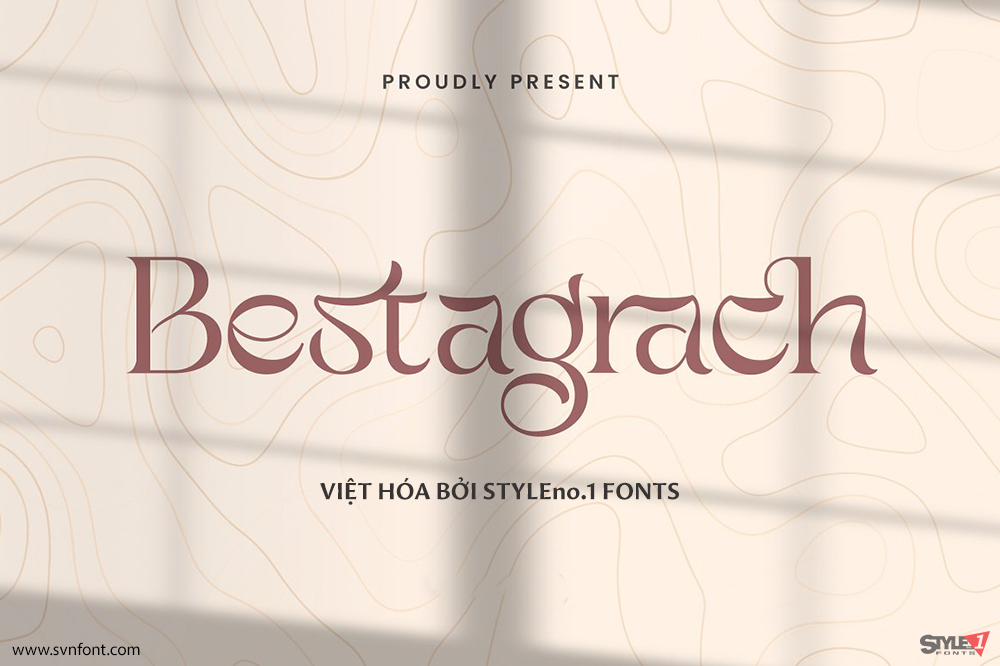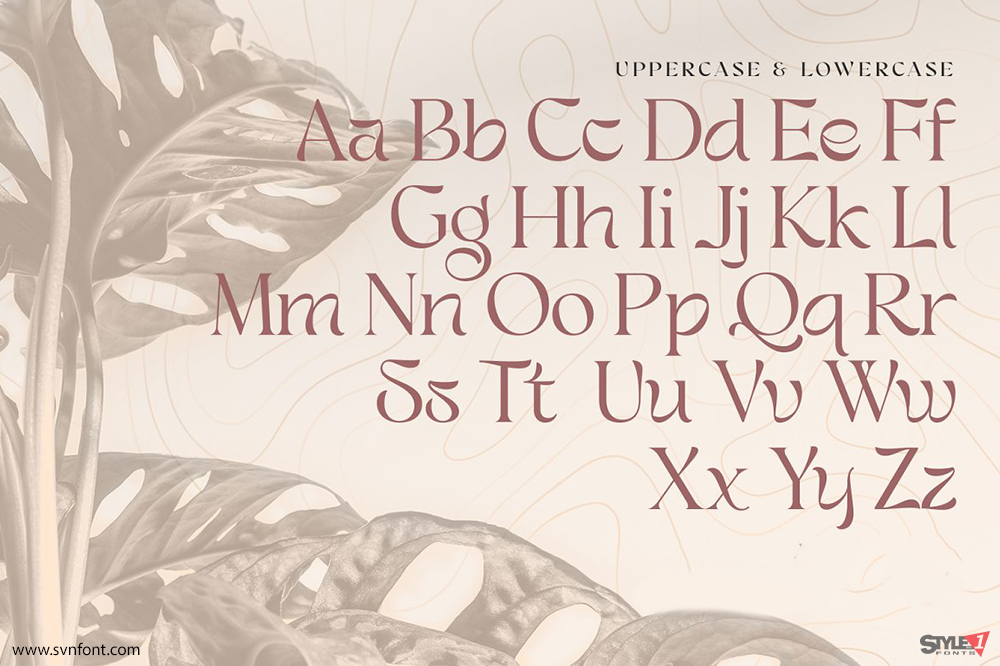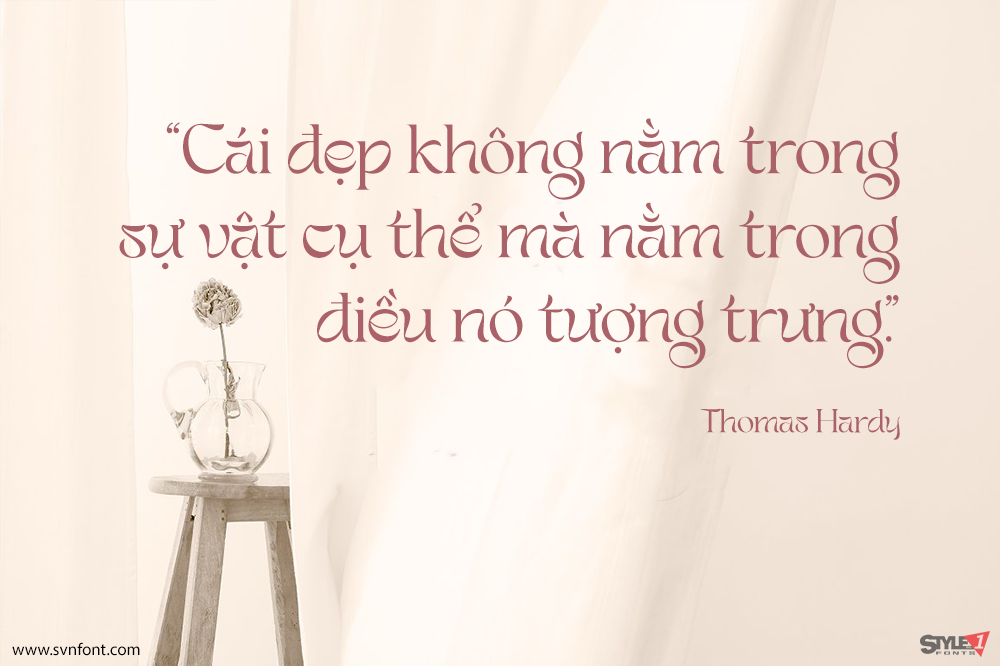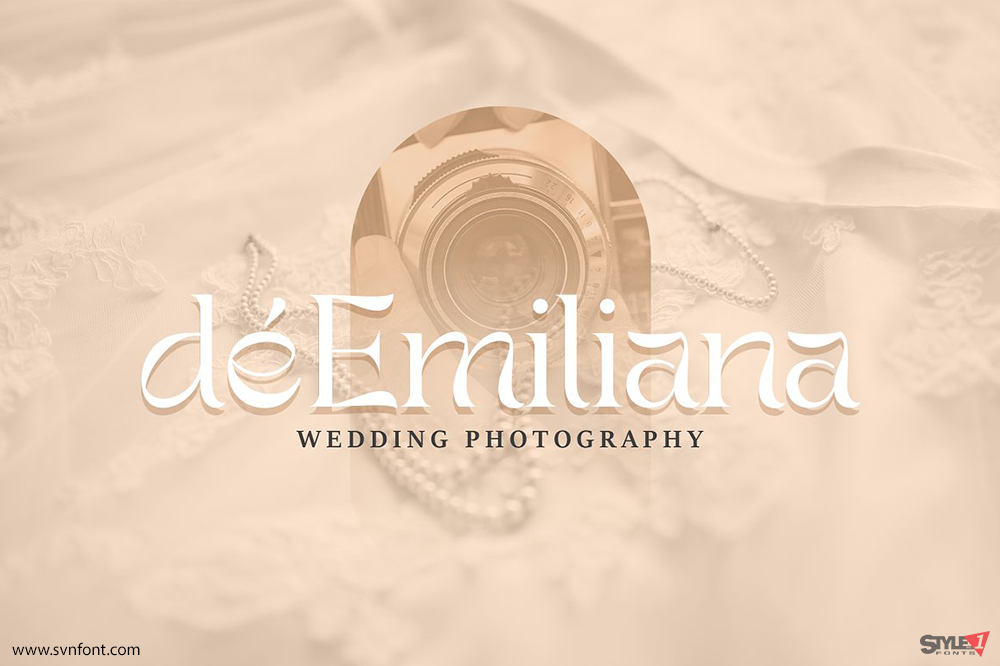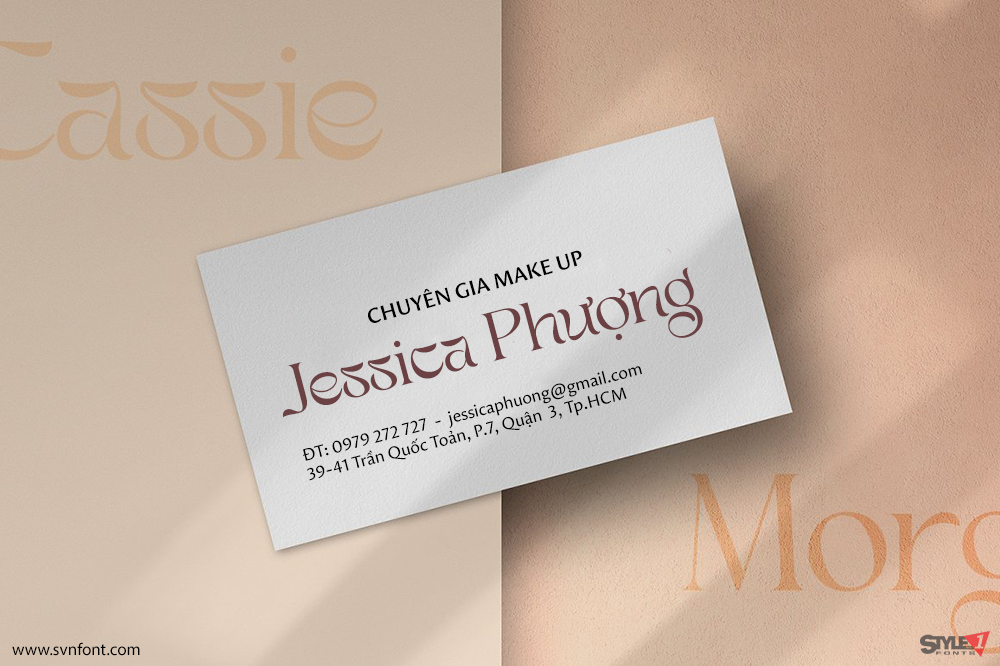
Font Việt Hóa SVN-Bestagrach Chữ Nối Sáng Tạo
Bestagrach - Chữ nối độc đáo Connected Serif là một phông chữ thanh lịch và sử dụng các chữ ghép để liên kết các chữ cái một cách trơn tru. Hoàn hảo để thêm một nét độc đáo cho biểu trưng đánh dấu từ, chữ lồng hoặc dấu ngoặc kép. Bestagrach có 12 chữ ghép và làm cho nó trở nên siêu tuyệt vời. Có thể tắt dấu nối nếu nhu cầu viết chuẩn được yêu cầu.
Nhà thiết kế: Mokatype Studio
Nhà phát hành: Mokatype Studio
Việt hóa: STYLEno.1 Fonts